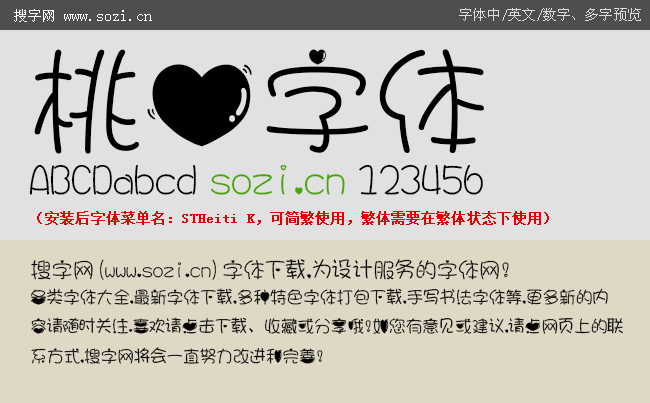
桃心字體
搜字網(wǎng)給大家提供一款很卡通的手機(jī)中文字體下載。修改者將它命名為桃心字體,這款手機(jī)字體是以仿照兒童手寫風(fēng)格的卡通手寫字體為原形,將個(gè)別筆畫替換成了可愛的卡通心形圖案。即有卡通字體的趣味性,又有手寫字體的藝術(shù)性,特別適合喜歡手機(jī)字體個(gè)性一些的朋友在手機(jī)上安裝使用。